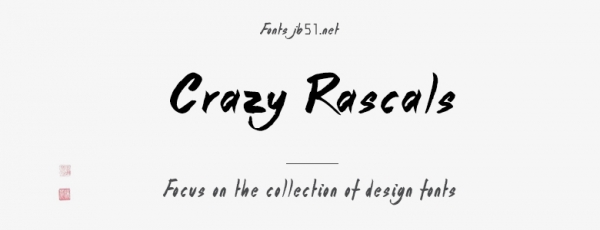
Crazy Rascals英文手寫(xiě)字體
Crazy Rascals英文手寫(xiě)字體,字體筆觸適中,具有很好的視覺(jué)感,適合應(yīng)用于藝術(shù)設(shè)計(jì)、平面宣傳設(shè)計(jì)、網(wǎng)頁(yè)設(shè)計(jì),書(shū)法字帖等領(lǐng)域,需要的朋友可以前來(lái)本站下載。